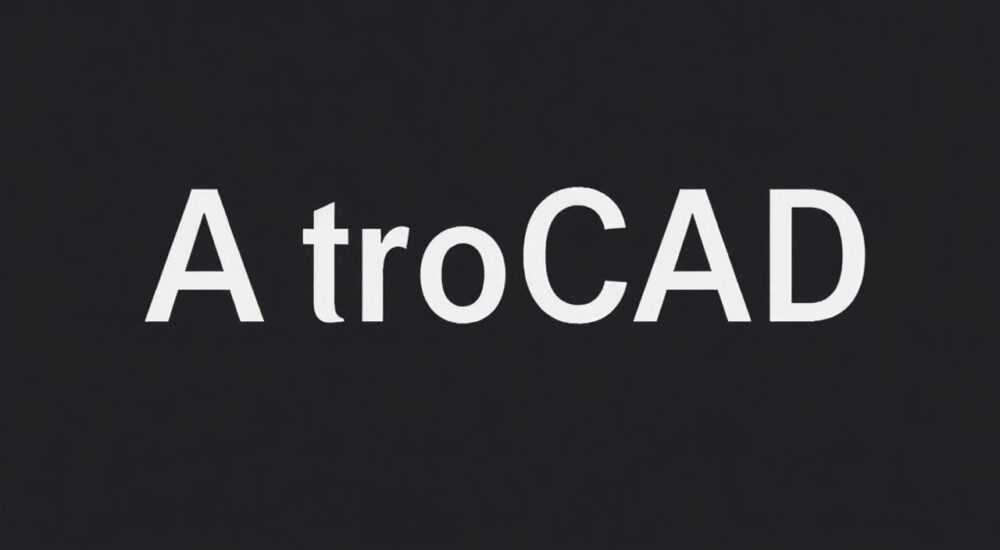
Как в автокаде изменить шрифт текста
Изменение шрифта текста в AutoCAD — базовая, но критически важная операция для обеспечения читаемости и соответствия документации стандартам. Это можно сделать как для отдельных надписей, так и для всех текстовых объектов через стили. Основной инструмент — редактор текста и диспетчер стилей, позволяющие быстро заменить шрифт, размер, выравнивание и другие параметры.
В профессиональном проектировании внешний вид текста влияет не только на эстетику чертежа, но и на его соответствие ГОСТам и требованиям заказчиков. Неправильный шрифт может вызвать вопросы при согласовании документации, особенно в строительстве, машиностроении и архитектуре. AutoCAD предоставляет гибкие инструменты для управления текстом: от простого редактирования отдельных меток до глобальной замены через стили. Владение этими функциями позволяет сэкономить часы работы и избежать ошибок при подготовке финальных чертежей.
Как изменить шрифт у отдельного текста
Если вам нужно изменить шрифт только одного или нескольких текстовых объектов, AutoCAD предлагает несколько способов. Наиболее быстрый — использование контекстного редактора. Выделите нужный текст двойным щелчком мыши или выберите его и нажмите Enter. Откроется вкладка «Редактирование текста» на ленте, где можно изменить шрифт, размер, цвет и другие параметры.
Альтернативно, воспользуйтесь панелью «Свойства» (Ctrl+1). В ней отображаются все характеристики выделенного объекта. Найдите параметр «Шрифт» и выберите нужное значение из выпадающего списка. Этот метод особенно удобен, если вы работаете с многострочным текстом (MTEXT) или хотите точно контролировать каждый параметр.
- Двойной клик по тексту — открывает встроенный редактор.
- Панель «Свойства» — даёт полный контроль над атрибутами.
- Лента «Главная» → «Текст» — позволяет быстро применить предустановленные стили.
Обратите внимание: если текст создан как однострочный (DTEXT), его возможности ограничены. Рекомендуется использовать MTEXT — он поддерживает форматирование, переносы строк и работу со стилями. При редактировании через панель свойств изменения применяются мгновенно, без необходимости подтверждения.
Пошаговый алгоритм изменения шрифта у одного объекта
- Выберите текстовый объект на чертеже.
- Нажмите клавишу Enter или дважды щёлкните по нему.
- В открывшемся редакторе найдите поле «Шрифт».
- Выберите нужный шрифт из списка (например, «romans.shx» или «Arial»).
- Закройте редактор, нажав «Закрыть текст» или кликнув вне области редактирования.
Этот способ идеален для разовых правок, но неэффективен при работе с большим количеством текста. Если вы меняете шрифт вручную у десятков объектов, стоит задуматься о переходе на стили.
Работа со стилями текста: основа эффективного редактирования
Стили текста — это ключевой механизм управления внешним видом надписей в AutoCAD. Вместо того чтобы менять каждый объект по отдельности, вы создаёте стиль (например, «Основной текст», «Примечания», «ГОСТ») и применяете его ко всему проекту. При изменении стиля все связанные с ним тексты автоматически обновляются.
Для доступа к стилям используйте команду STYLE или перейдите на вкладку «Аннотации» → «Текст» → «Диспетчер стилей текста». Здесь вы можете создавать, редактировать и удалять стили. Каждый стиль включает параметры:
- Имя стиля;
- Шрифт (SHX или TrueType);
- Высоту;
- Ширину (масштаб);
- Наклон;
- Обращение (перевёрнутый текст);
- Выравнивание.
Параметр |
Описание |
Рекомендации |
Шрифт |
Выбор SHX (векторный) или TTF (растровый) |
Для ГОСТ — romand.shx; для презентаций — Arial |
Высота |
Фиксированная высота текста |
Установите 0, если хотите задавать высоту при вводе |
Ширина |
Масштаб по горизонтали |
1.0 — стандартное значение |
Наклон |
Угол наклона символов |
Используйте редко, только при необходимости |
Создание нового стиля:
- Откройте «Диспетчер стилей текста».
- Нажмите «Новый», задайте имя (например, «ГОСТ_2026»).
- Выберите шрифт: для технической документации подойдёт «gostica.shx» или «simplex.shx».
- Установите высоту 2.5 или 3.5 мм (в зависимости от масштаба печати).
- Подтвердите создание.
Как применить стиль к существующему тексту
Если текст уже создан, но используется другой стиль, его можно переназначить:
- Выделите объекты.
- Откройте панель «Свойства» (Ctrl+1).
- Найдите параметр «Стиль текста».
- Выберите нужный стиль из списка.
Все выделенные тексты примут новые параметры. Это особенно полезно при импорте чертежей из других источников, где использовались чужие стили.